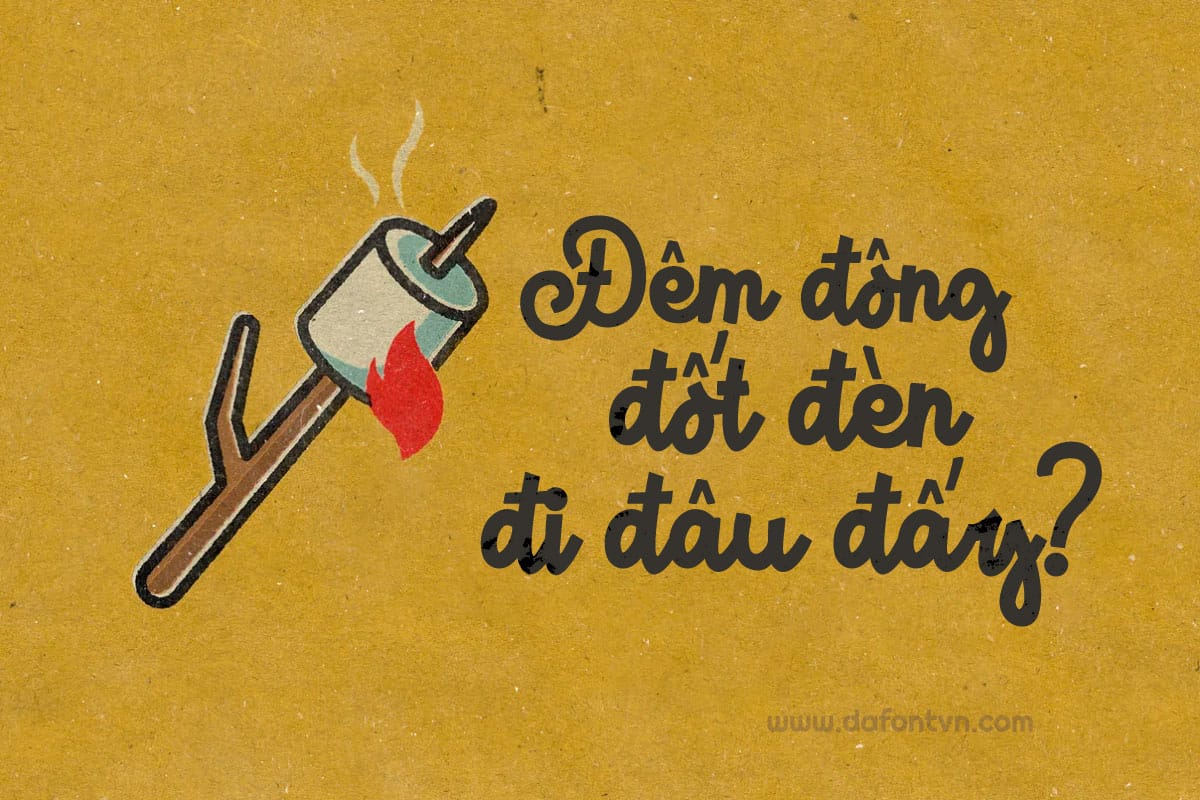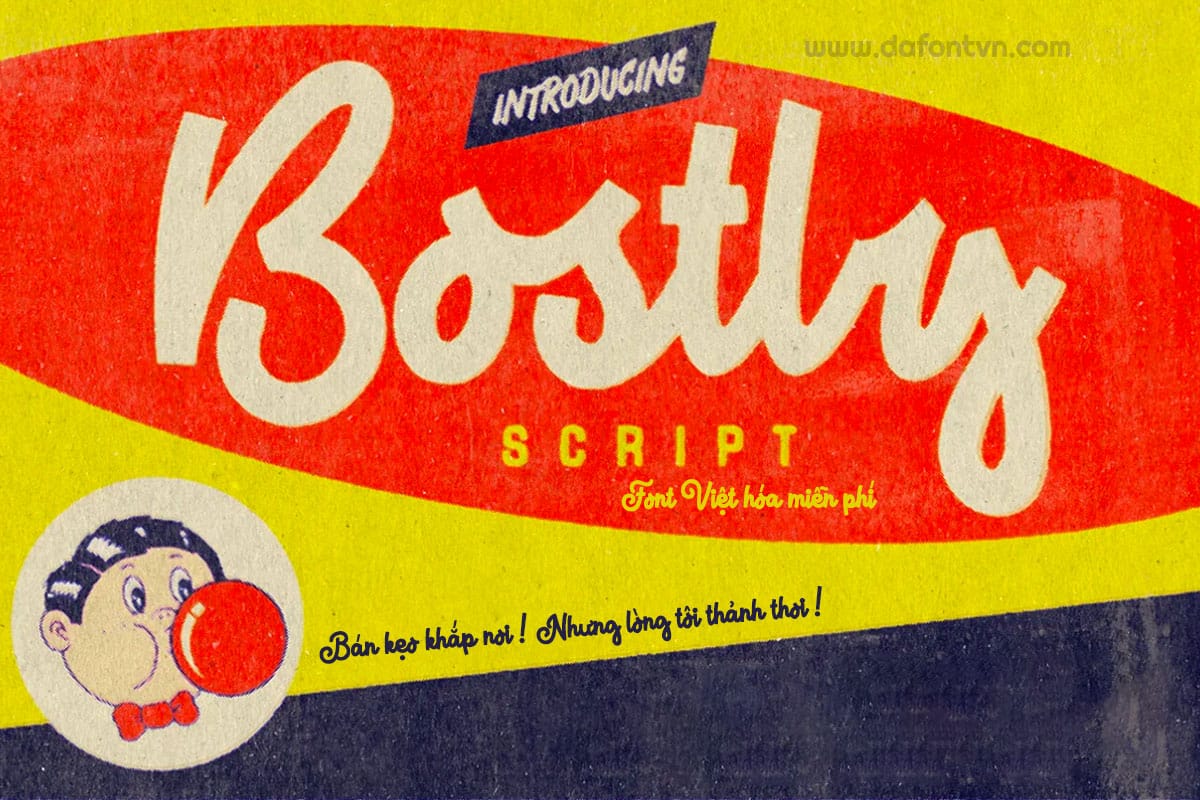
Font iCielBC Bostly Script Việt hóa miễn phí nằm trong bộ font iCiel Nam Kỳ Diễn Ca được Việt hóa và chia sẻ miễn phí bởi iCiel.
Font Bostly lấy cảm hứng từ kiểu chữ xưa cũ trên thiết kế áp phích / bao bì và nhãn xe từ những năm 1920 đến những năm 1980.
Nó đi kèm với một bộ hoàn chỉnh gồm: Chữ hoa, chữ thường, các số, dấu câu và hỗ trợ đa ngôn ngữ, tính năng Opentype.
Font chữ Bostly Script Việt hóa hoàn hảo cho áp phích, đồ họa áo phông, nghệ thuật sắp chữ, may mặc, thiết kế logo, bao bì, nhãn mác và những người font chữ xưa cũ.